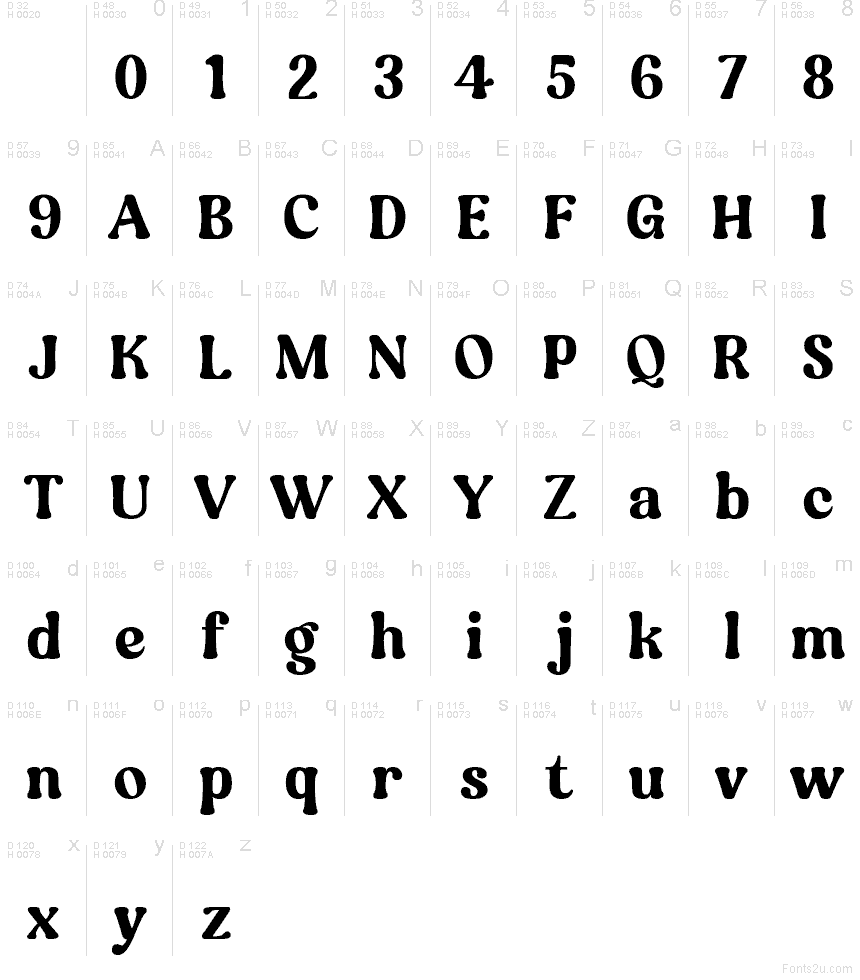
Midcent Disco, da Sixtype Foundry, é uma fonte display retrô gratuita que traz o suingue marcante das letras da vida noturna dos anos 1970. Serifas amplas e abertas, somadas a curvas encorpadas, dão às letras uma silhueta suave, quase derretida. As variações na espessura dos traços são marcantes, mas os contornos irregulares mantêm as formas acolhedoras, sem parecerem excessivamente polidas.
Uma loja de discos, um bar de coquetéis ou uma marca de roupas vintage podem utilizá-la para construir uma identidade de época consciente e marcante. A fonte também se adapta muito bem a cartazes de festivais e capas de álbuns. Nesses contextos, seu volume macio e suas curvas teatrais unem música, moda e noite ao glamour vibrante da era disco e à publicidade gráfica clássica de meados do século XX.